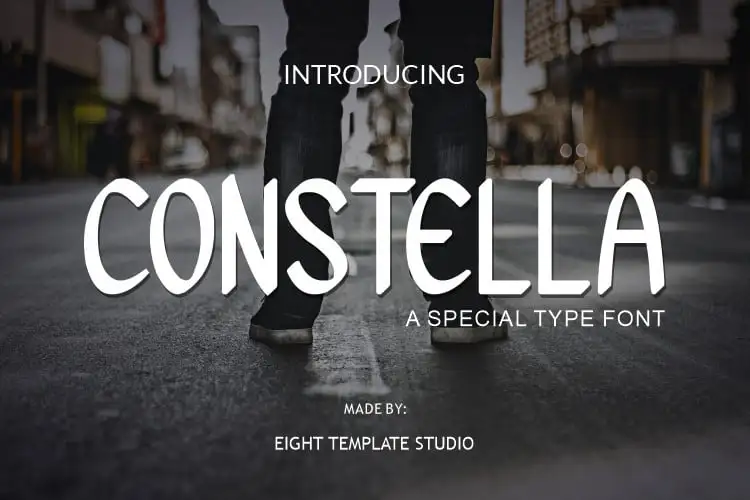
Constella Script Font – Download Grátis
Constella Script Font é uma deliciosa tipografia feita à mão, suave e delicada que vai deixá-lo apaixonado por sua versatilidade inigualável. Ela é ideal para criar cartões de casamento incrivelmente belos, arte de papelaria elegante, posts de mídia social chamativos e muito mais. Este fonte é perfeito para personalizar seus projetos digitais, trazendo uma sensação delicada que reflete o amor pelo trabalho artesanal. Engaje-se com a Constella Script Font e transforme suas ideias em obras de arte exuberantes.
Designer: kumsstudio